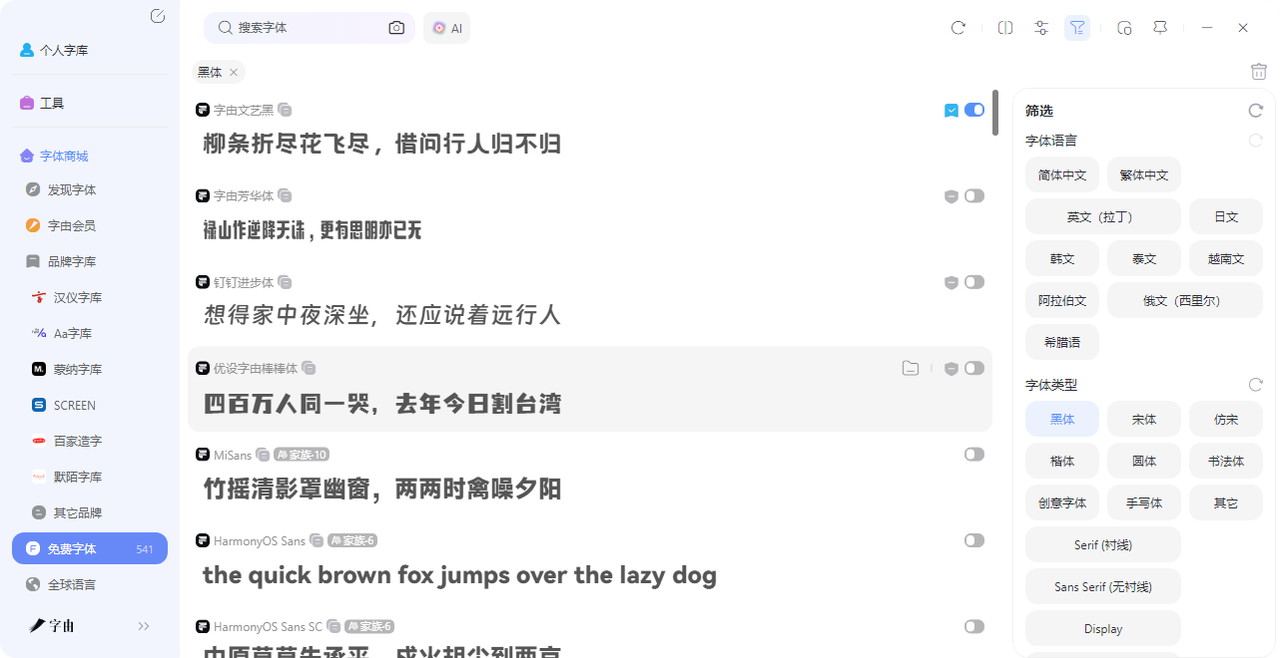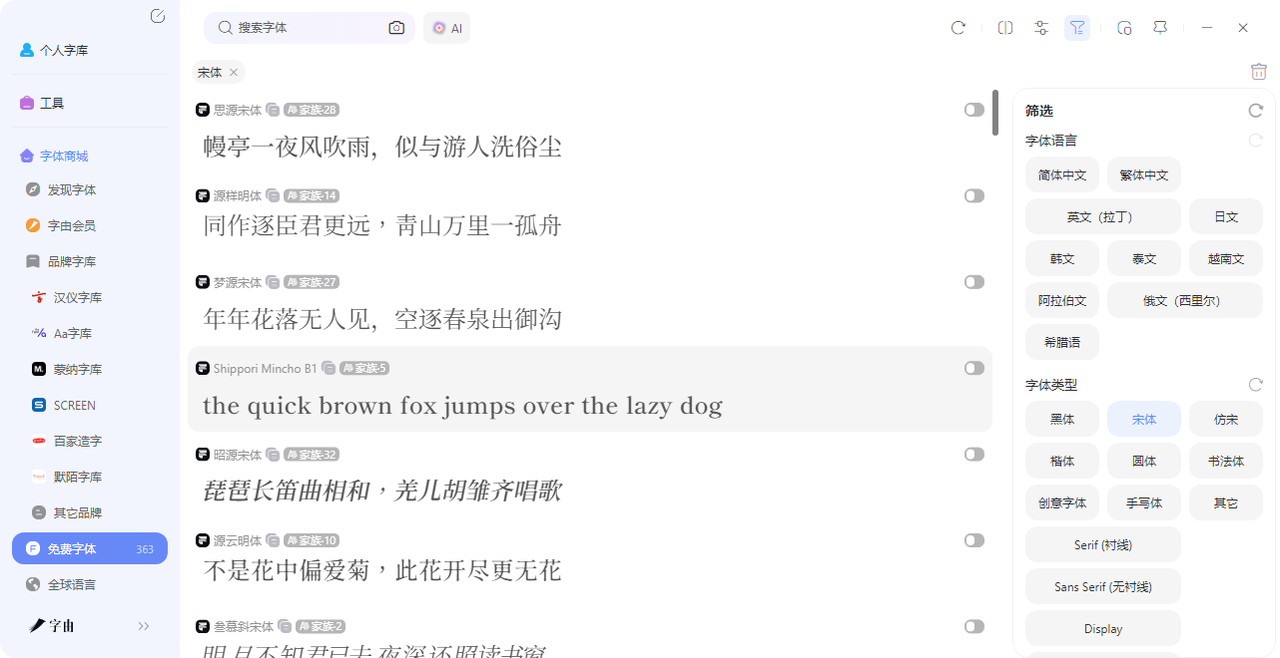
设计小白必看:字体有哪些种类?字由带你入门
很多新手其实在做设计的时候不会考虑字体有什么分类,大部分都是觉得“这个好看,用这个就行”。但事实上是当我们想要在设计领域深耕的话,就必须去了解字体的设计原理,以及字体的基础分类都有哪些,这样也方便后续提高自己的设计能力。那么今天我就用字由这个字体平台当例子,一边看它的字体分类体系,一边把字体的种类和特点讲明白。看完这篇,下次选字体的时候你就知道该往哪个方向找了。
1、字体基本概念
聊具体种类之前,有两个基础概念得先弄明白——衬线体 和 无衬线体。这两个词是所有字体分类的起点,不管中文还是英文,都绕不开。衬线体(Serif),最简单的理解方式就是“有装饰”。仔细看宋体这种字体,笔画开始和结束的地方会多出一些小修饰,而且横竖笔画粗细不一样。这种设计让文字在长篇阅读时更容易辨认,所以很多书、报纸、杂志的正文都爱用衬线体。
无衬线体(Sans Serif)刚好反过来,没有那些装饰,笔画粗细差不多,线条更简洁利落。黑体就是典型代表,干净、现代、好识别,现在很多 App 的界面、网站正文、海报标题都偏爱这一类。
简而言之,衬线体像穿了正装,优雅正式;无衬线体像穿 T 恤,清爽干练。搞懂这个,再看下面的具体分类就容易多了。
2、字由的字体分类,按风格怎么分
现代派
黑体也叫等线体,属于前面说的无衬线字体。它的特点是去掉了所有装饰,笔画简洁大方,粗细均匀,整体感觉干净、现代、有力量感。适合用在标题、导语、UI 界面这类需要清晰传达信息的场景。字由里的黑体资源相当丰富,从思源黑体这种开源经典,到字由文艺黑这类自有品牌,都能轻松找到。
传统派
宋体是有衬线字体的代表,笔画横细竖粗,起笔和收笔的地方带着装饰性的小三角,自带一种“正式感”和“书卷气”。做画册、书籍排版、古风设计的时候,宋体往往是首选。字由里收录了大量宋体类字体,从汉仪、方正等大厂的经典作品,到各种小众设计师的创意宋体,选择面很广。就连我们平时写文档也会首选宋体。
书法派
书法体模拟毛笔书写的效果,有行书、草书、楷书、隶书等各种分支。这种字体自带艺术感和文化气息,适合用在需要表达“中国风”或者“手写温度”的场景,比如品牌 Logo、海报标题、国潮设计。字由里书法体的数量相当可观,还有专门的“书法体”筛选标签,进去就能看到一大片。
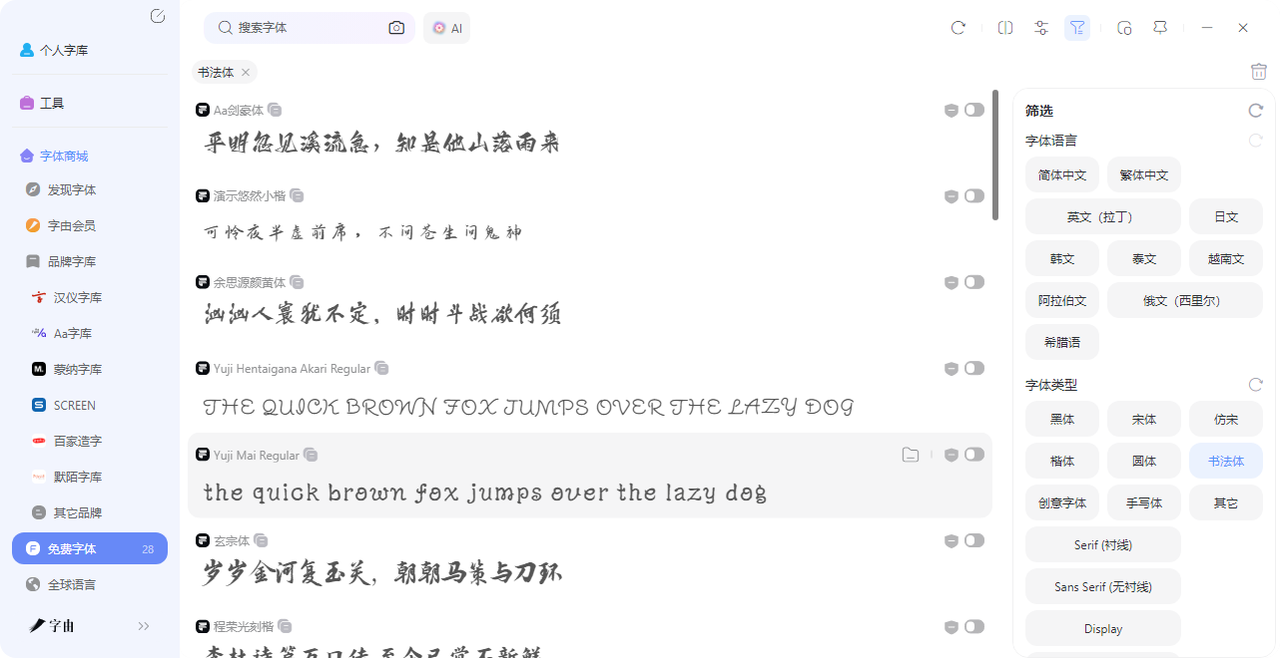
手写派
手写体和书法体容易混淆,区别在于:书法体强调的是毛笔书法的艺术性,而手写体更接近我们日常用笔写出来的字迹,可能不太规整,但真实、亲切、有个性。适合用在手账风、文艺风的海报或社交媒体配图上。字由收录了很多独立设计师制作的手写体,风格从工整到随性都有。
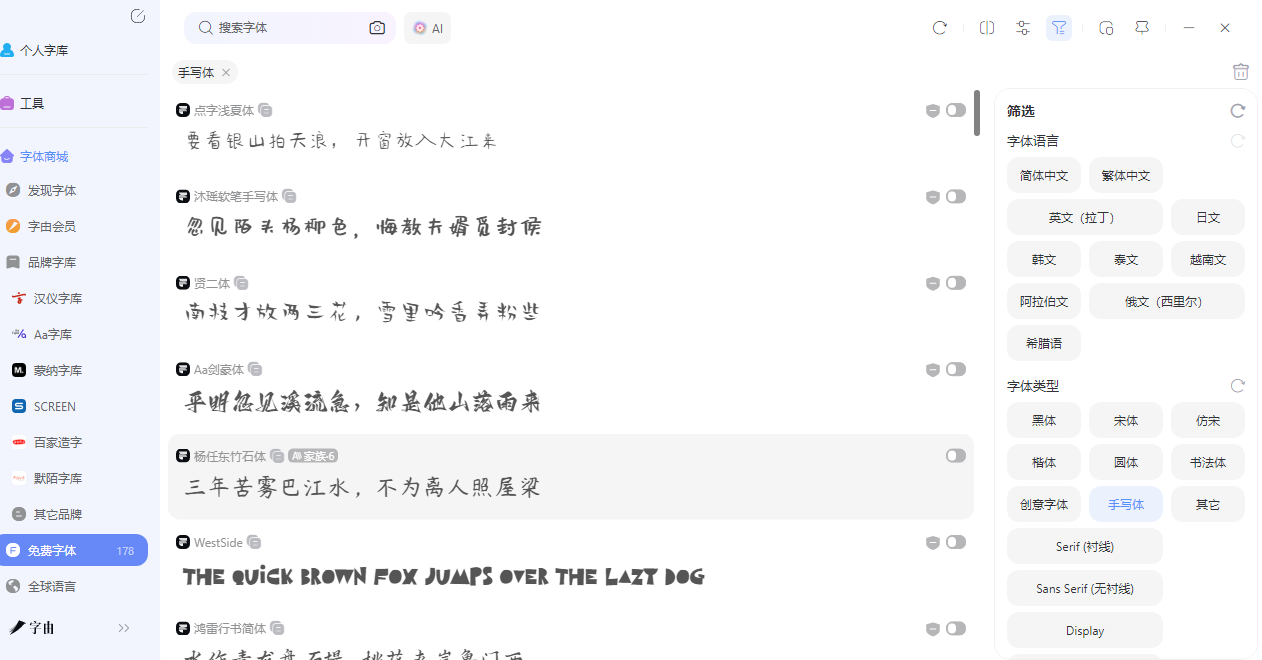
其他英文字体
字由不只是做中文字体。通过筛选栏里的“字体语言”标签,你可以按语言类别来浏览字体——简体中文、繁体中文、英文(拉丁)、日文、韩文、泰文、阿拉伯文、俄文(西里尔)、希腊语等。每种语言下的英文字体又可以根据风格进一步细分:有无衬线体、衬线体、手写体、显示体等。字由和蒙纳字库等全球顶级字体公司有深度合作,蒙纳旗下就有超过 15 万款字体,覆盖全球多种语言,很多世界级的经典英文字体——比如 Helvetica、Arial、Times New Roman——都能在字由找到。